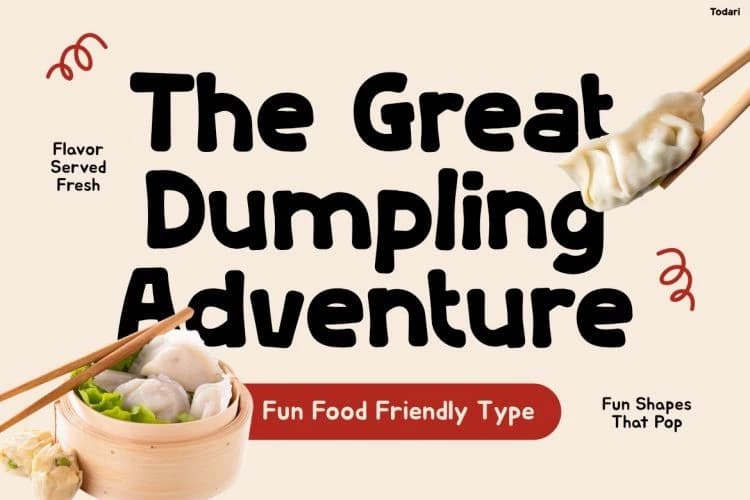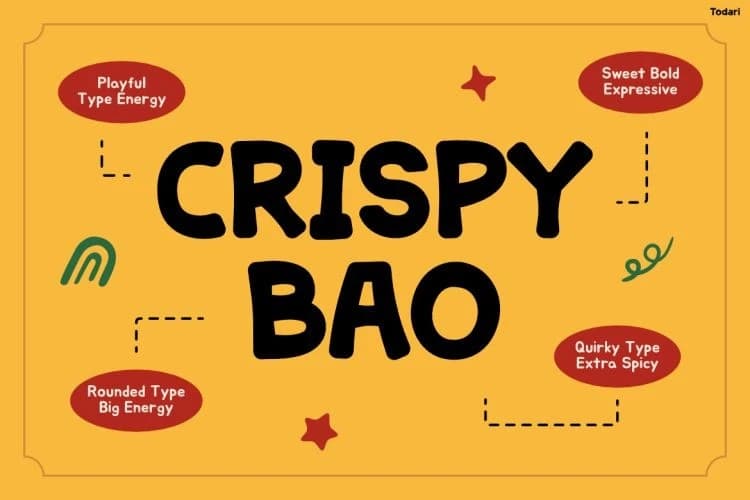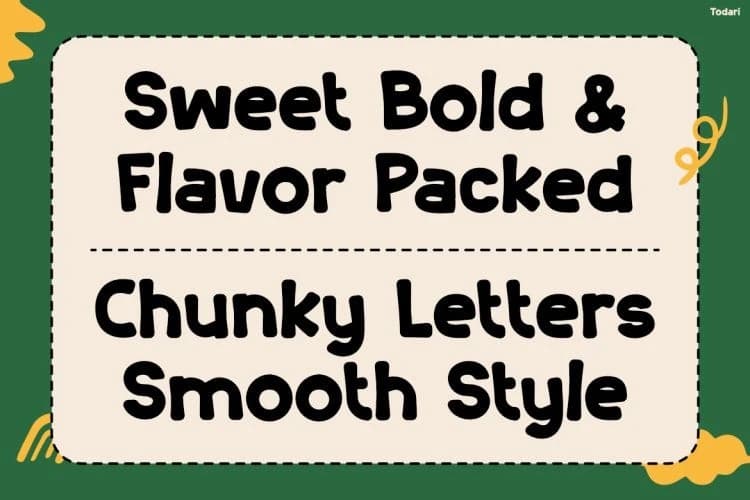
Todari Playful Font
Todari Playful Font, her tasarıma kalın, iri harf biçimleri, oyuncu eğriler ve yemeklerden ilham alan neşeli enerji katar. Ayrıca, kalın yuvarlak şekiller sevimli ve samimi bir görünüm yaratır ve hemen dikkati çeker.
Todari Playful Font, her tasarıma kalın harf biçimleri, oyuncu eğrileri ve yiyeceklerden ilham alan neşeli bir enerji getirir. Ayrıca kalın yuvarlak şekiller, hemen dikkat çeken sevimli ve dostça bir görünüm yaratır.